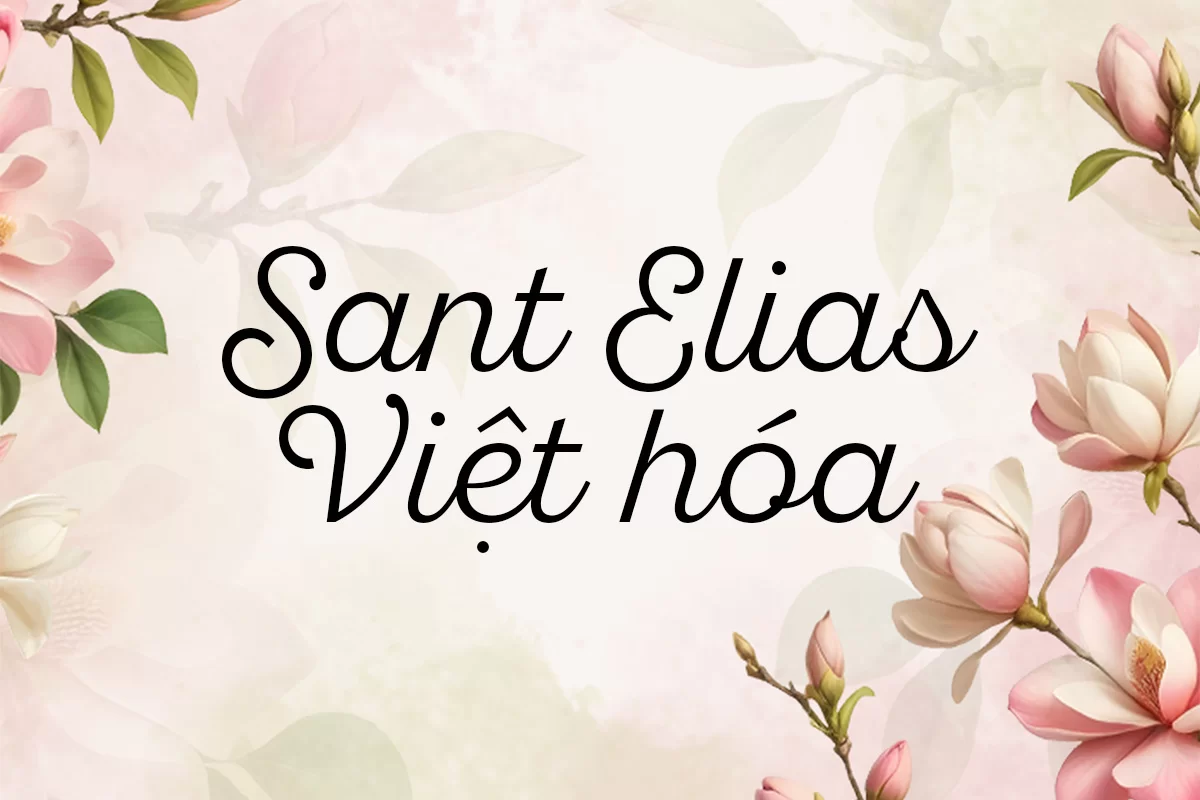
Sant Elias Việt hóa là một font chữ script mang phong cách viết tay thanh lịch, uyển chuyển nhưng vẫn giữ được sự rõ ràng và dễ đọc. Font có đặc trưng bởi những đường cong mềm mại, nét chữ tròn trịa kết hợp với độ dày vừa phải, tạo nên cảm giác gần gũi và tinh tế.
Khi được Việt hóa, Sant Elias hỗ trợ đầy đủ dấu tiếng Việt, đảm bảo tính thẩm mỹ đồng đều từ chữ cái gốc đến các ký tự có dấu. Điều này giúp font trở nên hữu ích cho thiết kế ấn phẩm, logo, thiệp mời, poster hay các dự án sáng tạo mang hơi thở thủ công và sang trọng.
Phong cách của Sant Elias vừa mang nét cổ điển nhẹ nhàng, vừa hiện đại, phù hợp cho các thương hiệu cần sự mềm mại, nữ tính nhưng vẫn tinh gọn và chuyên nghiệp.
Khi được Việt hóa, Sant Elias hỗ trợ đầy đủ dấu tiếng Việt, đảm bảo tính thẩm mỹ đồng đều từ chữ cái gốc đến các ký tự có dấu. Điều này giúp font trở nên hữu ích cho thiết kế ấn phẩm, logo, thiệp mời, poster hay các dự án sáng tạo mang hơi thở thủ công và sang trọng.
Phong cách của Sant Elias vừa mang nét cổ điển nhẹ nhàng, vừa hiện đại, phù hợp cho các thương hiệu cần sự mềm mại, nữ tính nhưng vẫn tinh gọn và chuyên nghiệp.